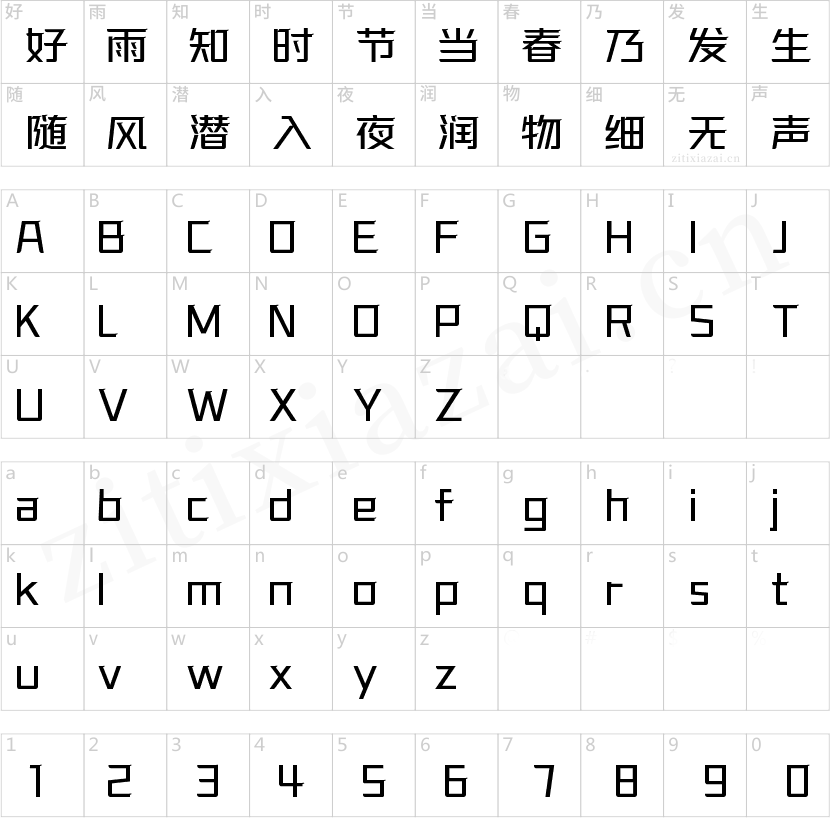
字魂正酷超级霹雳体
字魂字体字魂正酷超级霹雳体字体是由字魂创意字库设计并生产的一款可商用的字体,共8个字重,被收录于字魂先锋系列。该字体支持GB-2312标准以及最新的字魂ZH7144标准,包含7144个中文、字母、符号和数字,字体类型偏向黑体,具有活泼、时尚的风格,在市面上广泛用于教育培训、标题、视频影视等场景。